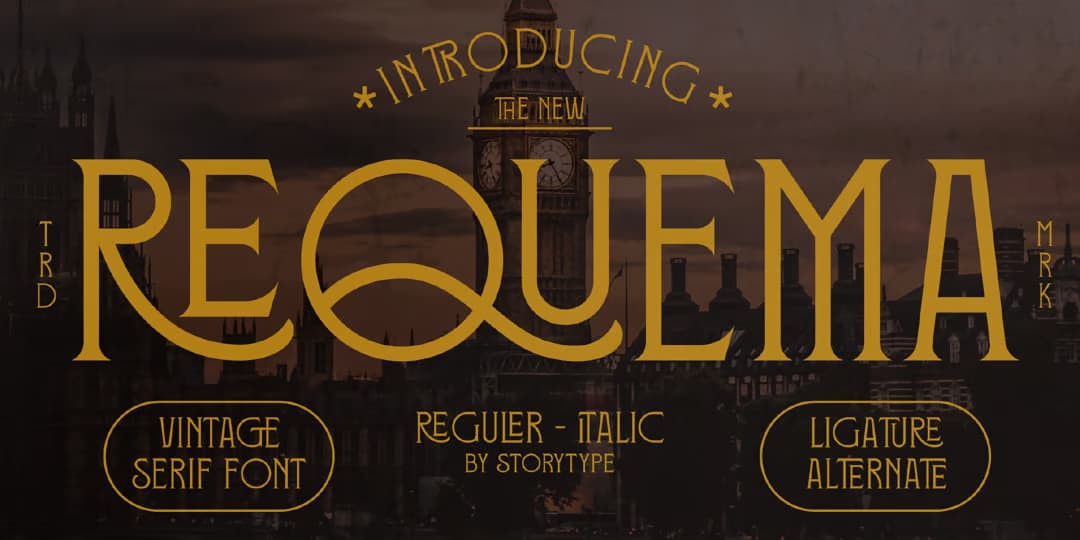
ヴィンテージ感のあるセリフドゴシックディスプレイ。セリフがあるので正しくはローマンなのだろうが、サンセリフ、それもアメリカでゴシックと呼ばれていたような頃の風味があるのでセリフドゴシックと呼ぶことにする。モノラインのジオメトリックなグリフに小さなセリフがちょこんと付いたレトロな雰囲気の書体で、見ての通りおもしろいリガチャーがそれなりにあって文字組みが楽しめるようになっている。大文字のみ書体だが、イタリックもあって2スタイル。